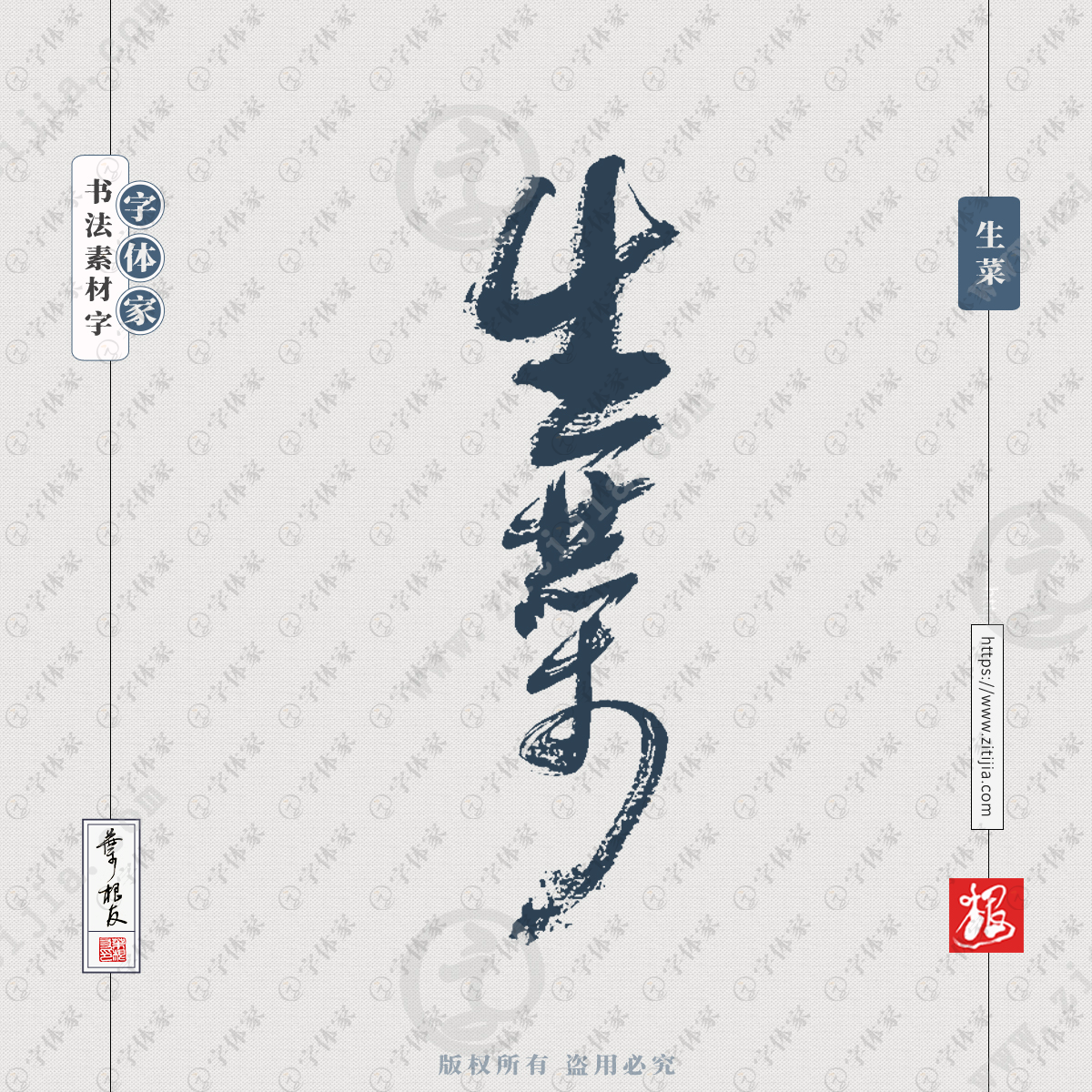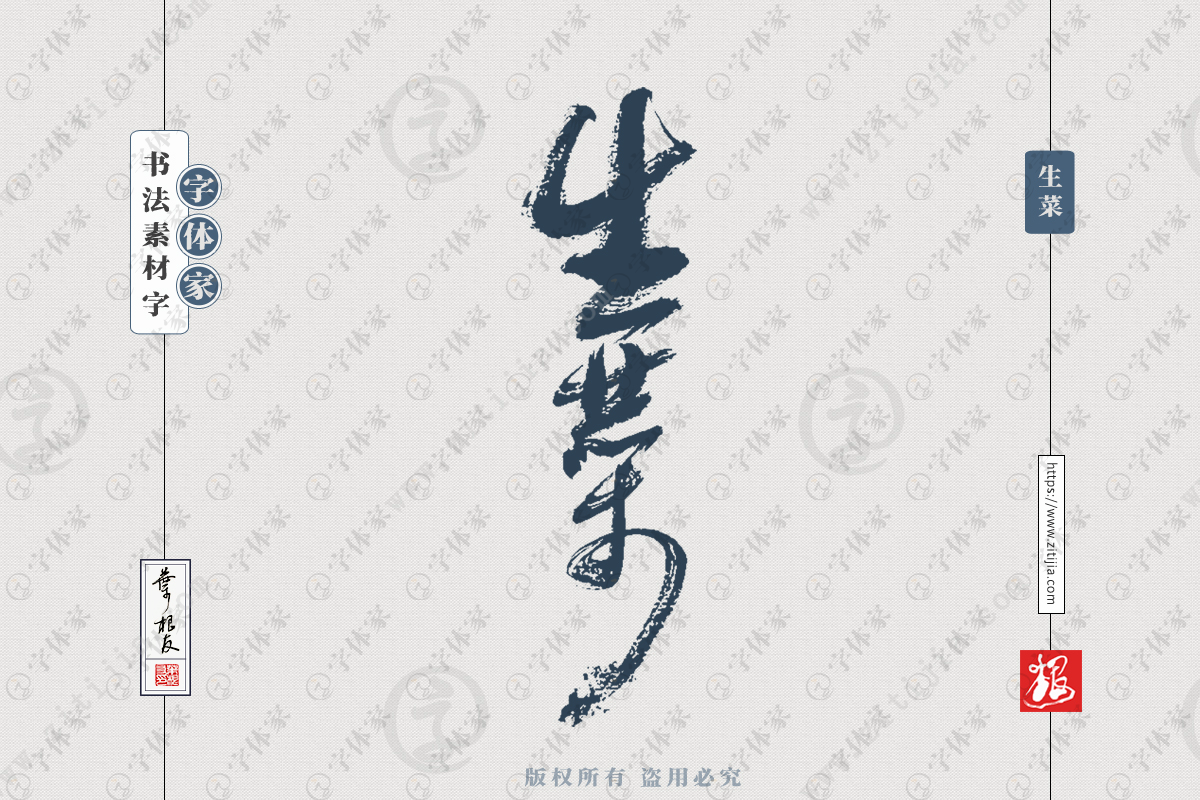
字体家提供生菜叶根友原创正版菜名蔬菜手写书法素材字体设计下载
生菜(Lactuca sativa L. var. ramosa Hort.)叶用莴苣的俗称,又称鹅仔菜、唛仔菜、莴仔菜,属菊科莴苣属。为一年生或二年生草本作物,叶长倒卵形,密集成甘蓝状叶球,可生食,脆嫩爽口,略甜。
生菜原产欧洲地中海沿岸,由野生种驯化而来。古希腊人、罗马人最早食用。
生菜传入中国的历史较悠久,东南沿海,特别是大城市近郊、两广地区栽培较多,近年来,栽培面积迅速扩大,生菜也由宾馆、饭店进入寻常百姓的餐桌。毒等。